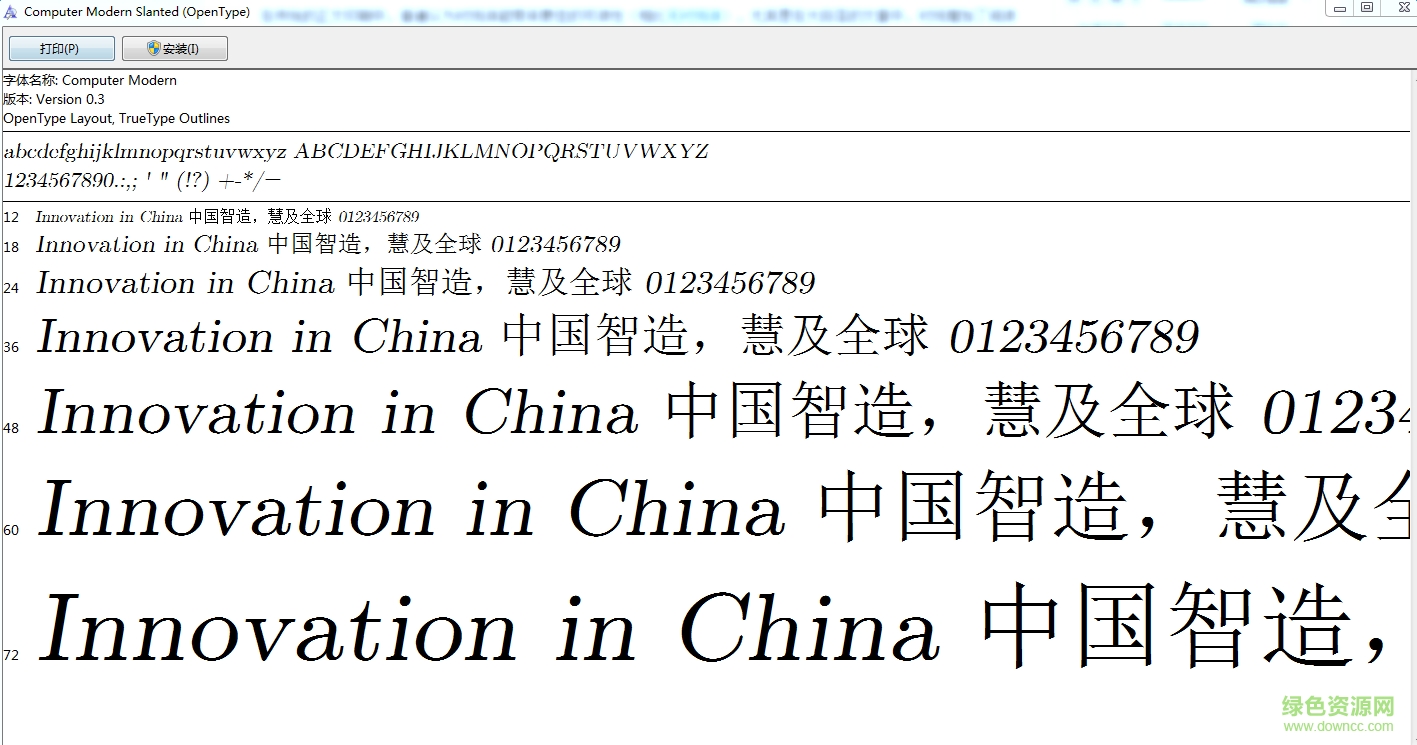
computer modern 字體
computer modern font是一款優(yōu)雅漂亮現(xiàn)代襯線體,姿態(tài)優(yōu)美,形態(tài)富于變化,精致又大氣,廣告效果非常好,有需要者歡迎在綠色資源網(wǎng)下載!
襯線體應(yīng)用趨勢
襯線體在書籍、報(bào)紙和雜志中大段落文字的排版,襯線體始終占據(jù)著壓倒性的優(yōu)勢。襯線字體在設(shè)計(jì)中占據(jù)很重要的位置。